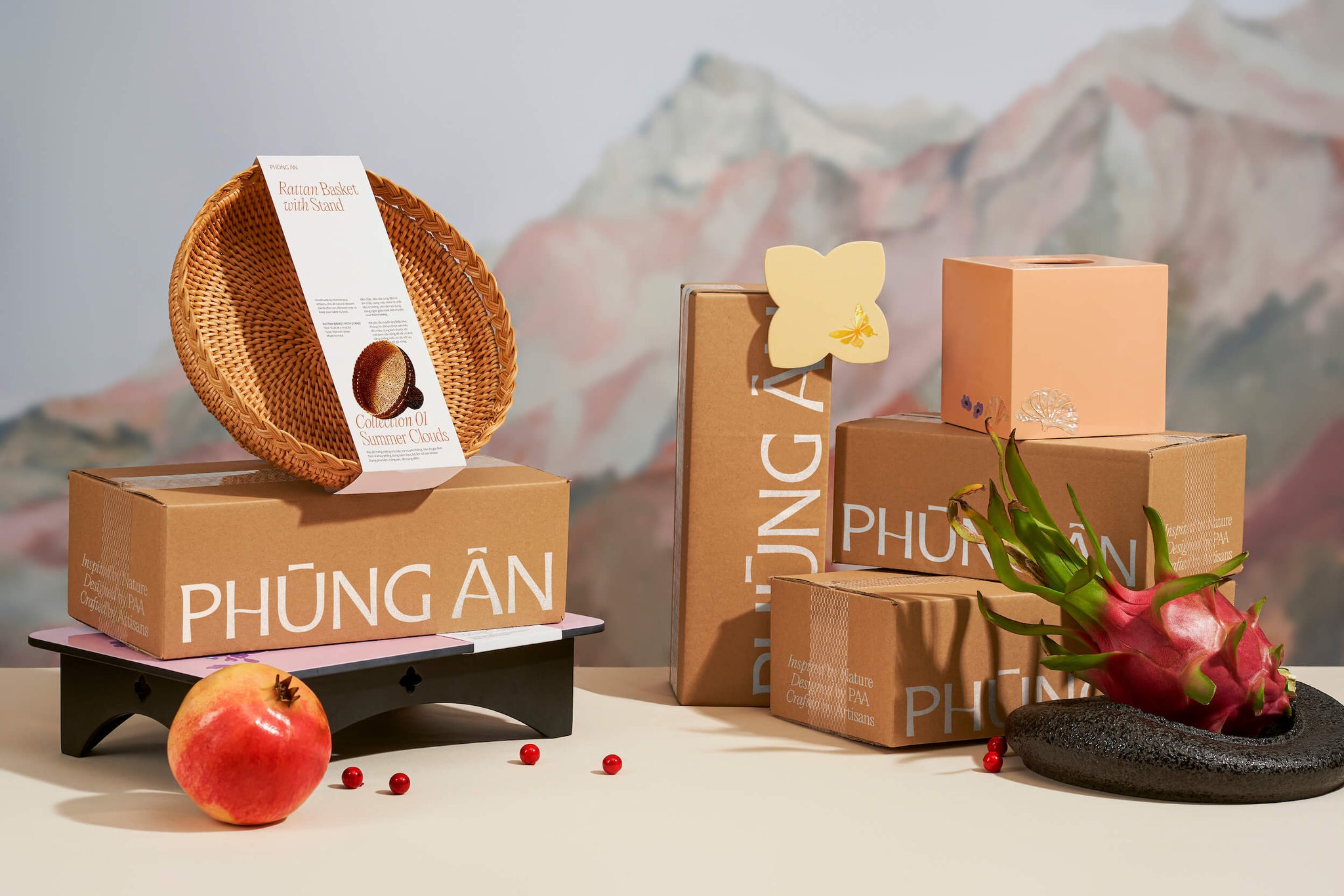
Phùng Ân Artisan propose des solutions d'articles ménagers de haute qualité, alliant inspiration locale et esthétique contemporaine.
Devenu un véritable fournisseur de cadeaux, Phùng Ân garantit la qualité artisanale de la conception à la production. Réputé pour sa créativité et son engagement durable, Phùng Ân revitalise l'artisanat vietnamien en soutenant les artisans locaux et en préservant le patrimoine culturel.
Phùng Ân a collaboré avec Layơ Lab pour revitaliser sa marque. L'objectif était de valoriser et d'unifier son identité visuelle, tout en affirmant son professionnalisme, sa modernité et sa créativité. En nous inspirant du quotidien et de la simplicité des artisans expérimentés et des villages artisanaux du Vietnam, nous avons puisé une mine d'inspiration et de matériaux pour la conception de nouveaux concepts.
En combinant des teintes jaunes traditionnelles (issues de l'artisanat traditionnel : terre ocre, bambou, bois d'ébène et papier doré) avec du papier kraft moderne et écologique, nous avons cherché à préserver et à sublimer le caractère rustique et traditionnel de l'artisanat vietnamien. De plus, ces matériaux sont utilisés pour emballer les produits artisanaux raffinés, livrés aux clients de Phùng Ân. Ainsi, ils honorent la valeur durable de l'artisanat vietnamien et préservent le patrimoine culturel pour l'avenir. De ces réflexions est né le concept de l'identité de marque de Phùng Ân Artisan : « Présenter le patrimoine culturel vietnamien pour l'avenir ».
Pour affirmer l'idée de durabilité et de lien avec l'artisanat traditionnel, l'élément visuel principal, la « poussière d'or », est introduit. Il est représenté par des patchs dorés de formes aléatoires sur la maquette, intégrant des couches d'images et de contenu. « Poussière d'or » symbolise l'héritage et met en valeur la valeur et la sophistication des produits, reflétant la qualité premium de la marque. Les détails dorés de « Poussière d'or » sont personnalisables en taille, en espace et en couleur, offrant une grande flexibilité d'application tout en soulignant les visions artistiques et contemporaines.
Le système d'image produit est également un élément clé de la différenciation de la marque, grâce à une interaction efficace et flexible avec un contenu textuel contrasté. Il met non seulement en valeur le savoir-faire artisanal de chaque produit, mais constitue également un outil de promotion et de vente pour la marque. Ensemble, ces produits forment une collection, mettant en valeur la beauté variée de l'artisanat vietnamien et mettant en valeur le portefeuille de produits de Phùng Ân. Dans certains cas, ces images peuvent être transformées en silhouettes en noir et blanc pour simplifier le design.
Pour allier tradition et modernité artistique, et souligner l'esprit de durabilité de la marque, l'identité visuelle de Phùng Ân Artisan intègre du papier kraft fait main associé à une impression blanche, créant une impression de modernité et de sophistication. Cette solution permet non seulement de réduire les coûts, mais aussi d'optimiser le design et d'ajouter une touche d'originalité à la marque. L'effet « Poussière d'or » sur papier kraft apporte douceur, délicatesse et sens, soulignant l'aspect « héritage » et apportant un intérêt et une modernité au design, insufflant une nouvelle approche. L'application d'une feuille d'or sur le texte et le fond crée des superpositions dans la mise en page, donnant de la profondeur au design.
"> Le contenu textuel est disposé en couches verticales, dans une mise en page spacieuse, accentuant le minimalisme. Le système typographique à fort contraste, dans un grand espace, apporte cohérence et lisibilité à l'ensemble du contenu. La mise en page se concentre sur le traitement des informations clés et la transmission de messages concis et directs. De plus, l'utilisation de l'italique pour la police Editorial New met en valeur les mots-clés, créant un style distinctif et captivant.